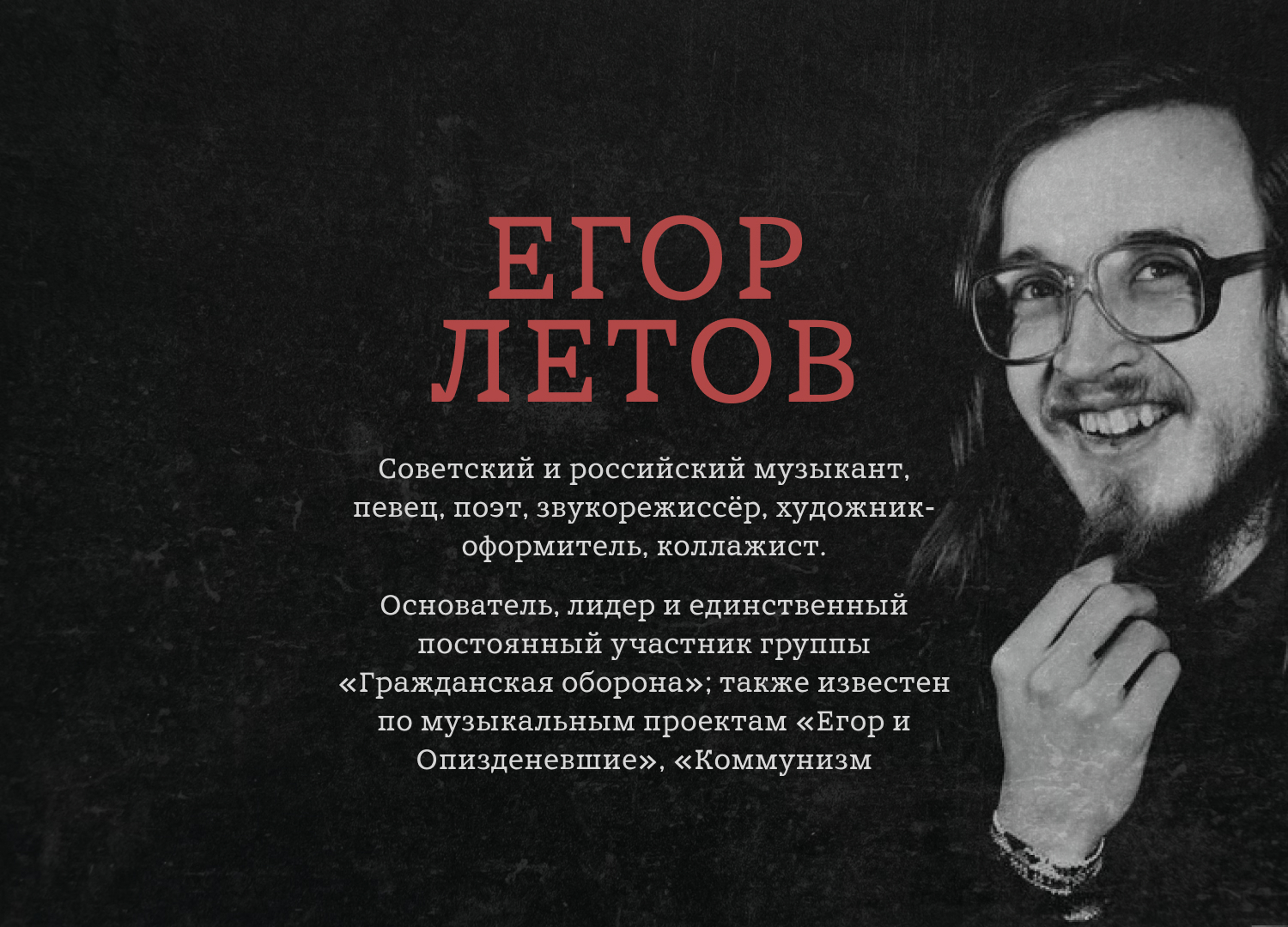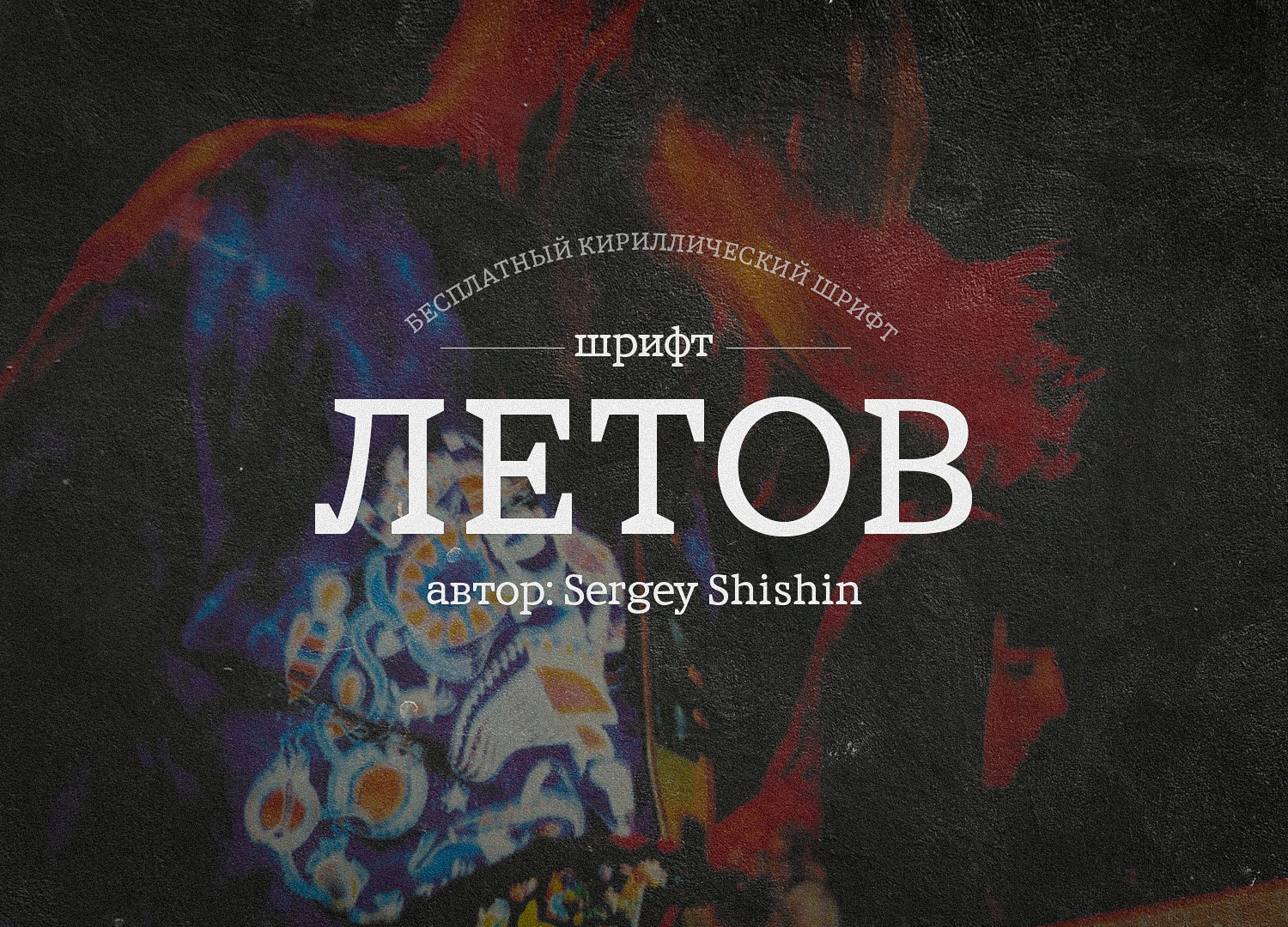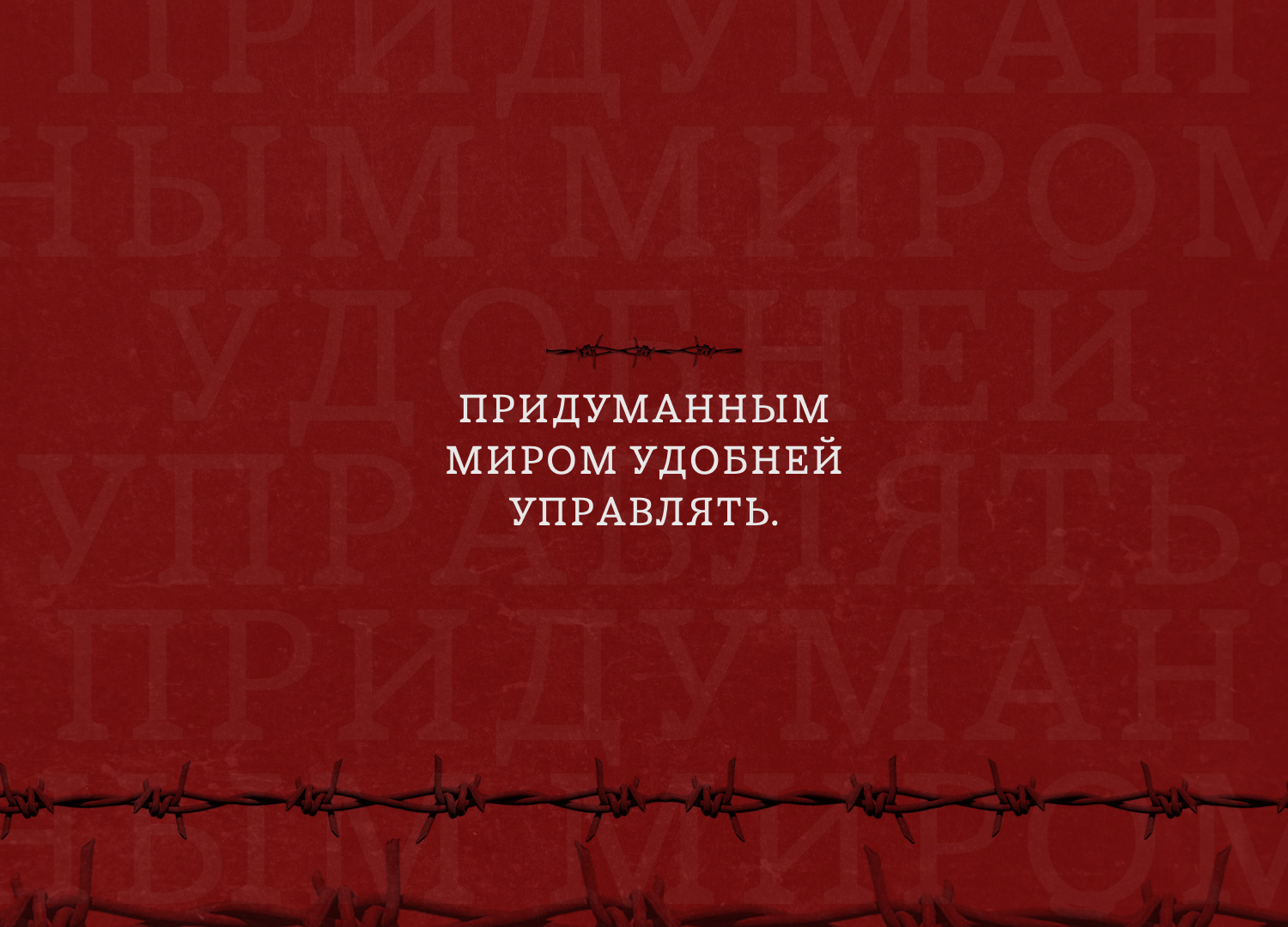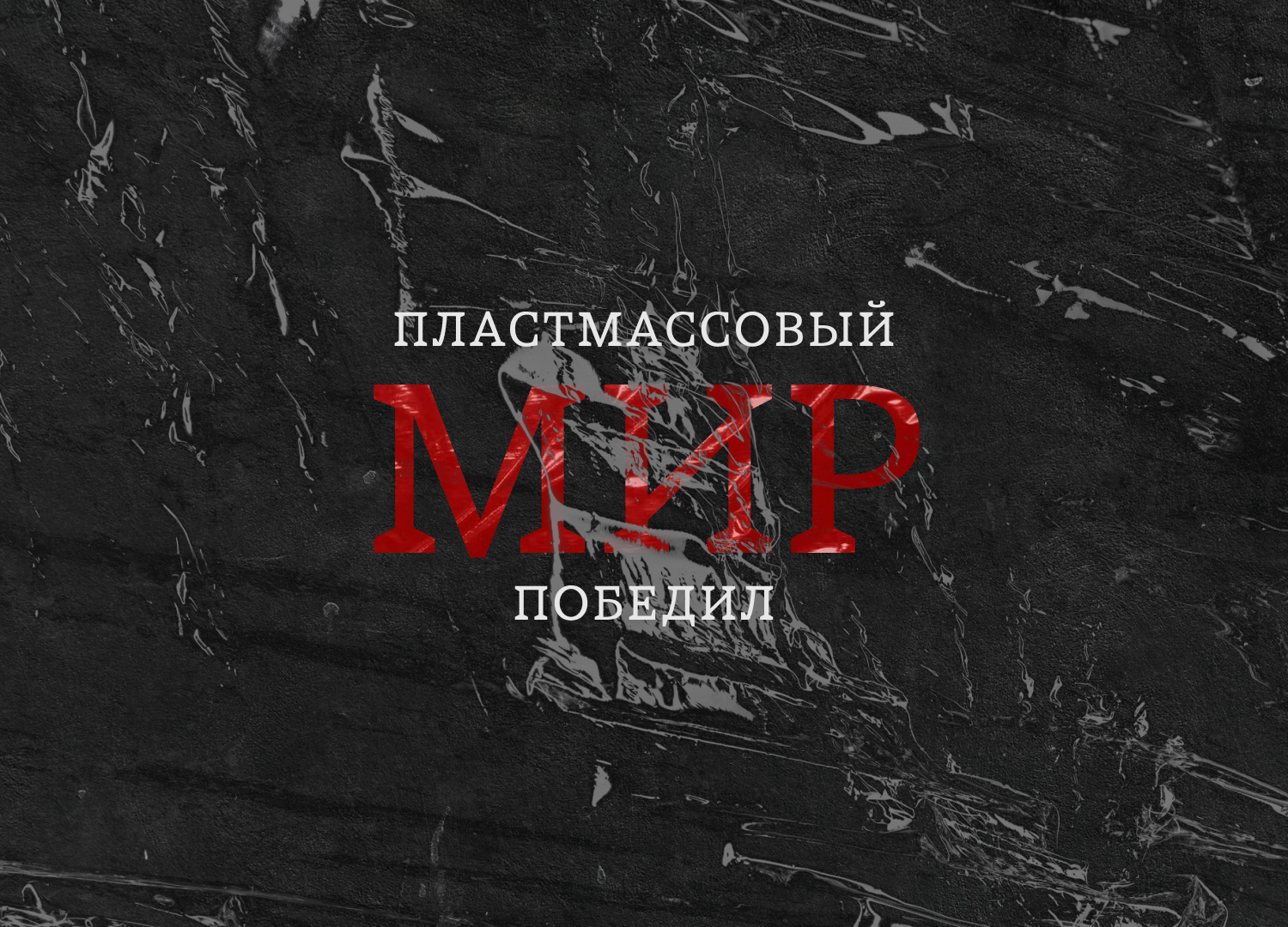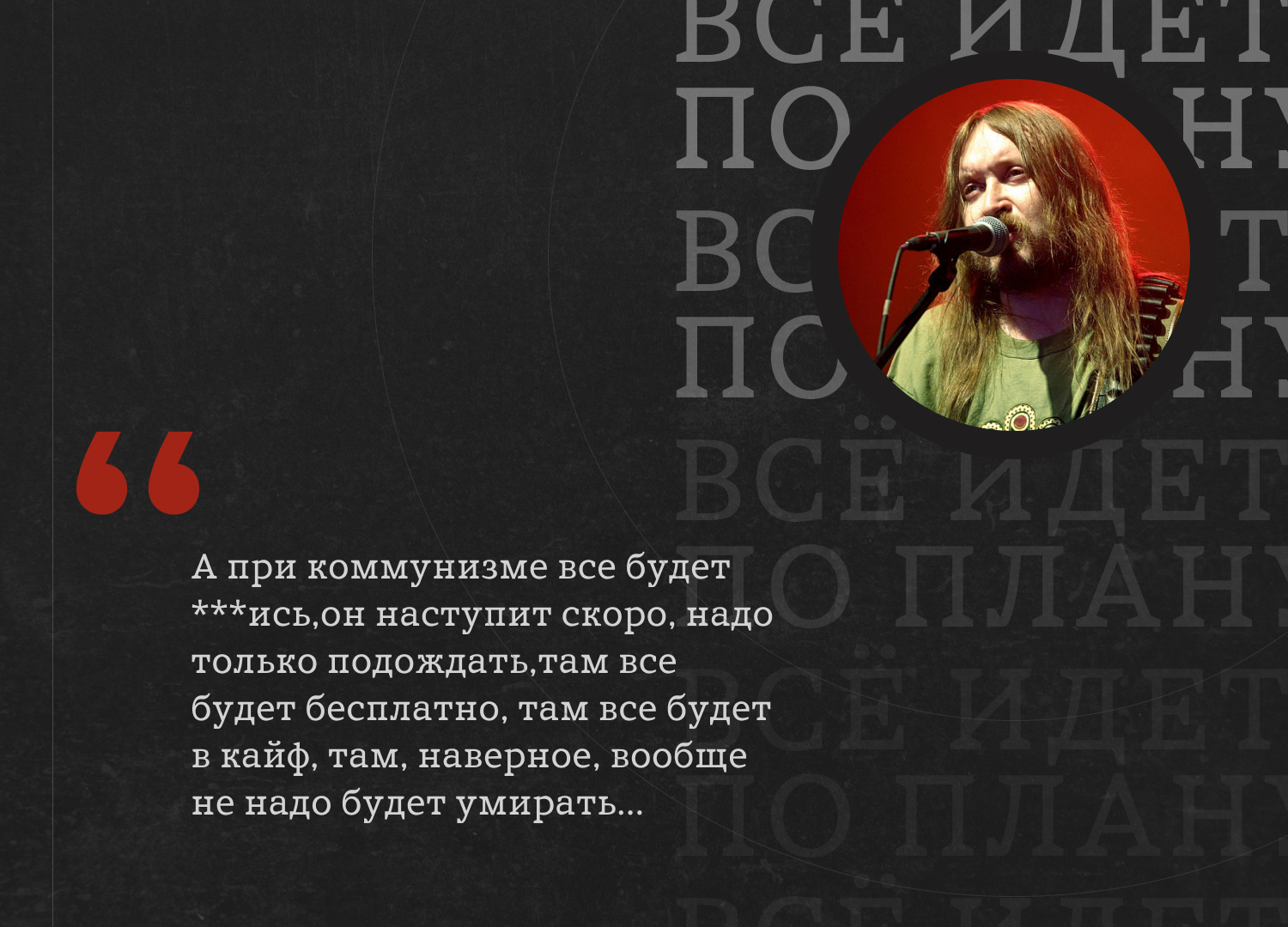
Шрифт Letov
Полностью бесплатный кириллический шрифт. Выразительный в заголовках и хорошо читаемый даже в мелком масштабе. Цитаты для презентации брал из песен «гражданской обороты», именем автора которой из назван шрифт.
Автор: Sergey Shishin.